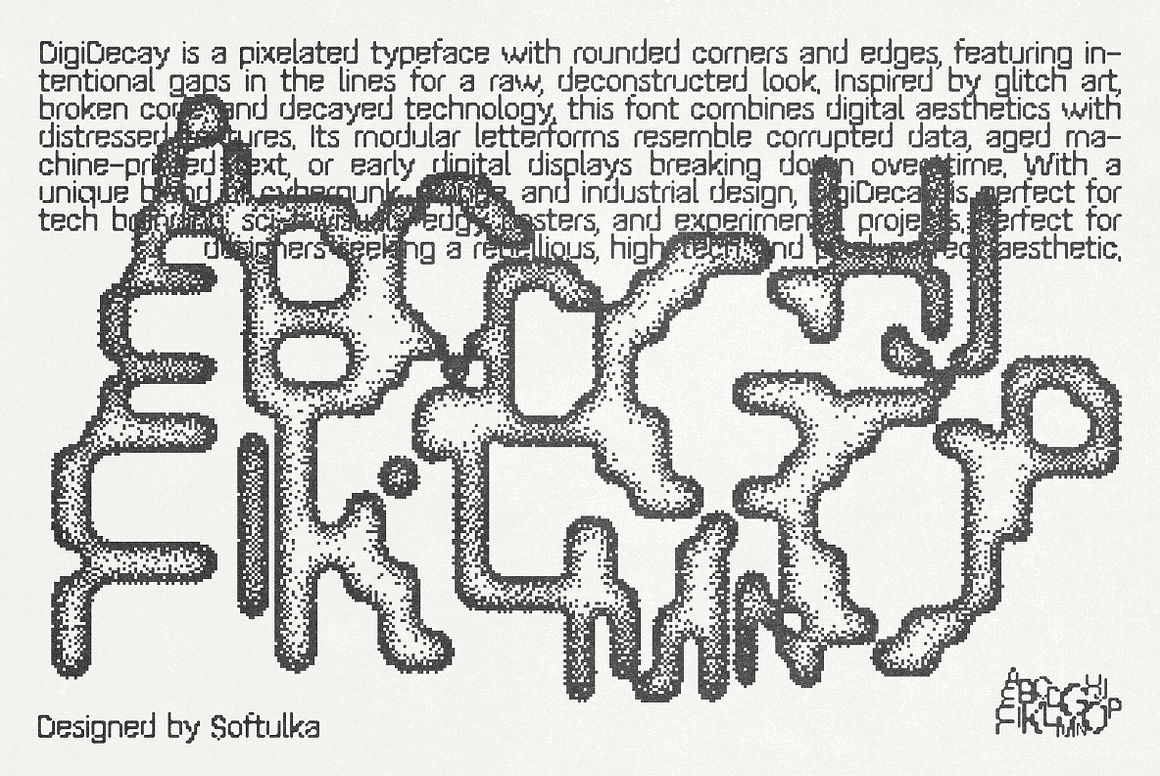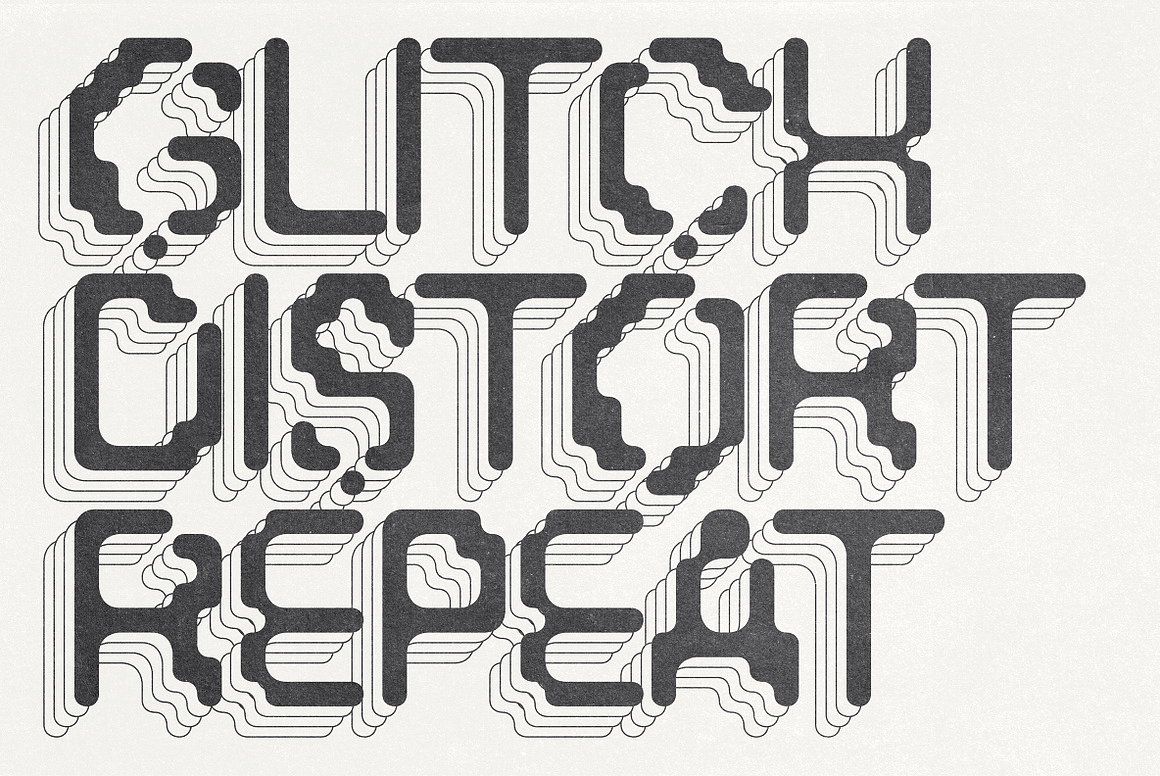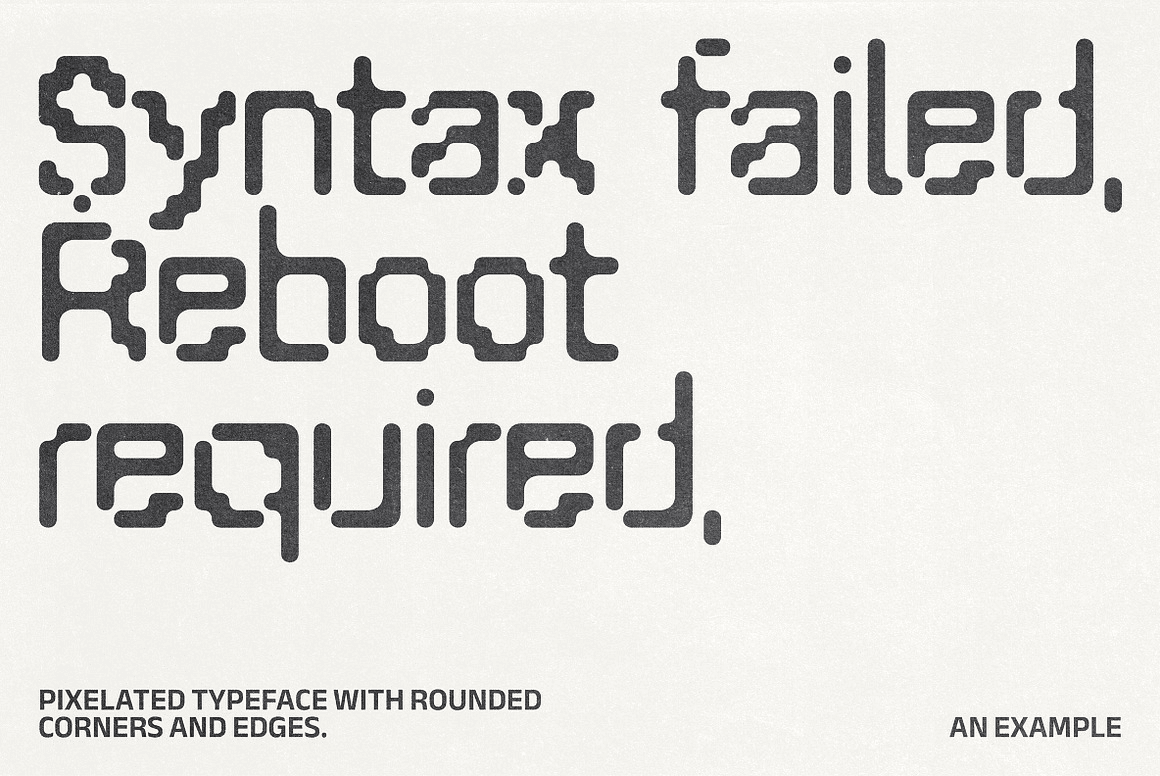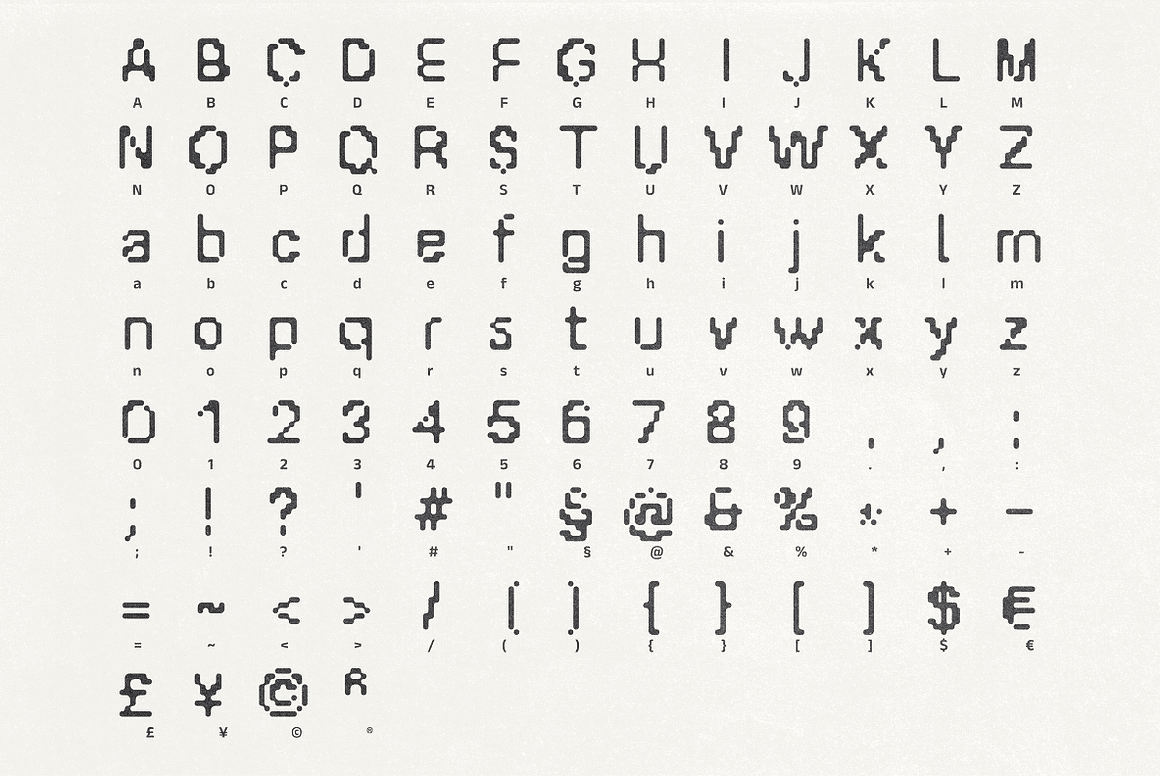
DigiDecay là một kiểu chữ pixel với các góc và cạnh được bo tròn, có các khoảng trống cố ý trong các đường kẻ để tạo vẻ ngoài thô ráp, bị phá vỡ. Lấy cảm hứng từ nghệ thuật glitch, mã bị hỏng và công nghệ suy tàn, phông chữ này kết hợp tính thẩm mỹ kỹ thuật số với các họa tiết bị mài mòn. Các hình dạng chữ mô-đun của nó giống như dữ liệu bị hỏng, văn bản in máy cũ hoặc màn hình kỹ thuật số ban đầu bị hỏng theo thời gian. Với sự pha trộn độc đáo giữa cyberpunk, grunge và thiết kế công nghiệp, DigiDecay hoàn hảo cho xây dựng thương hiệu công nghệ, hình ảnh khoa học viễn tưởng, áp phích góc cạnh và các dự án thử nghiệm. Hoàn hảo cho các nhà thiết kế đang tìm kiếm một thẩm mỹ nổi loạn, công nghệ cao và hoàn hảo đến từng pixel.